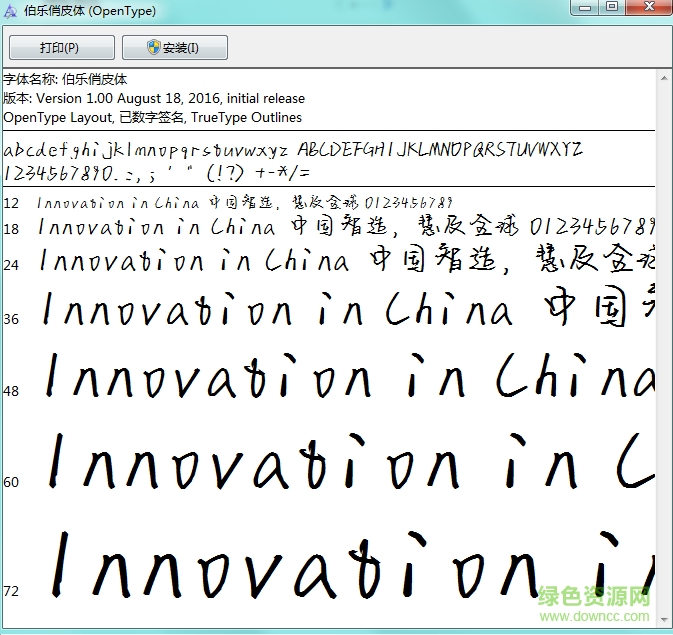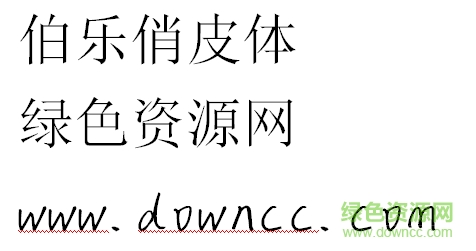
伯樂俏皮體
俏皮體是一款有著少女嬌俏特色的伯樂字體,簡(jiǎn)單秀氣又不失英氣蓬勃,是一款風(fēng)格迥異結(jié)合單別具美感的藝術(shù)字體,來(lái)綠色資源網(wǎng)即可免費(fèi)體驗(yàn)哦!
伯樂俏皮體字體介紹
俏皮體字體是一款用于可愛設(shè)計(jì)方面的字體,其中每個(gè)漢字都經(jīng)過(guò)精心設(shè)計(jì),筆畫 柔美光潔、粗細(xì)均勻、結(jié)構(gòu)美觀。每個(gè)字的圓角、圓頭、勾形都極光潔。
伯樂俏皮體也叫做伯樂軟妹體,是由伯樂花香體補(bǔ)全加粗后而來(lái),與伯樂軟妹體有著同樣的特色亮點(diǎn)。